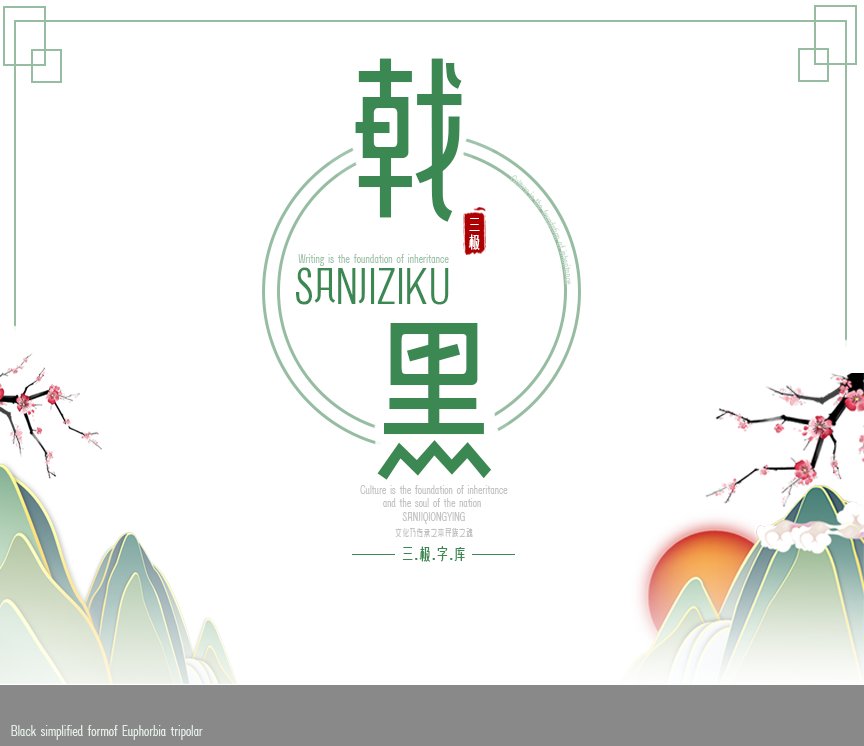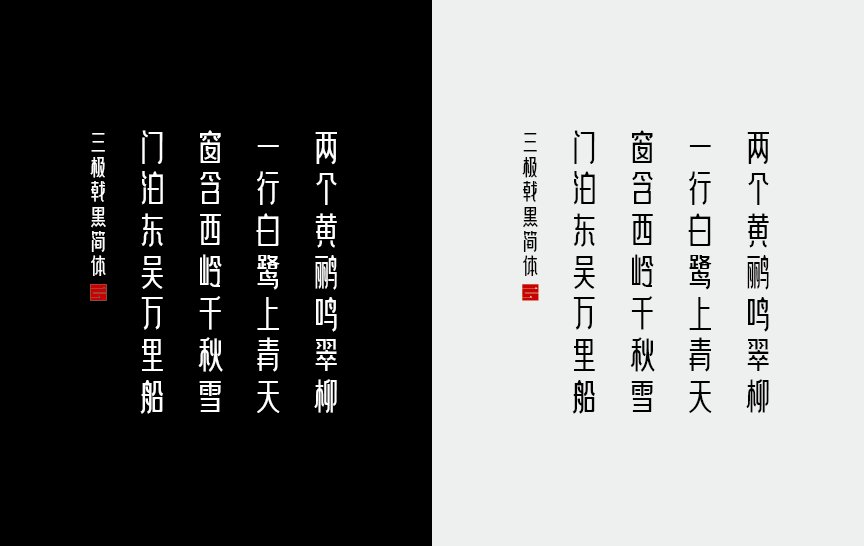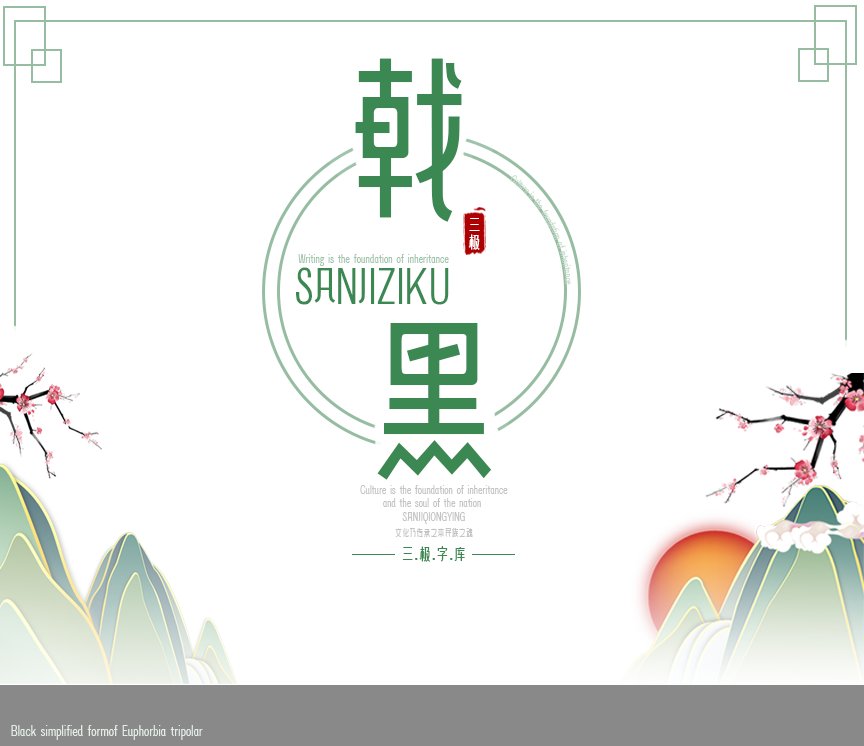
字体名称:三极戟黑简体
字体类别:黑体
字设计师:蔡建文,曹陆迎
适用场景:杂志、书籍、广告、标志、宣传册、包装、影视、动漫、屏幕显示、交互设计。
字库简介:三极戟黑简体灵感来源于商周文化,结合了冷兵器时期的建筑,服饰与青铜器的纹路而形成的三极戟黑简体,字体复古,极具商周色彩。适用于个性海报设计,复古风格包装设计等。